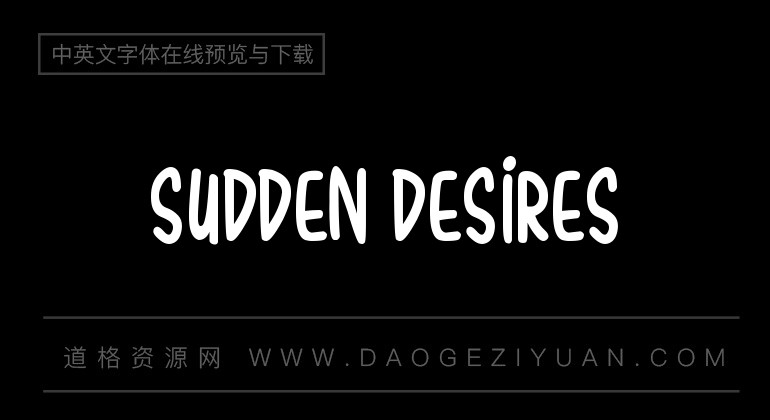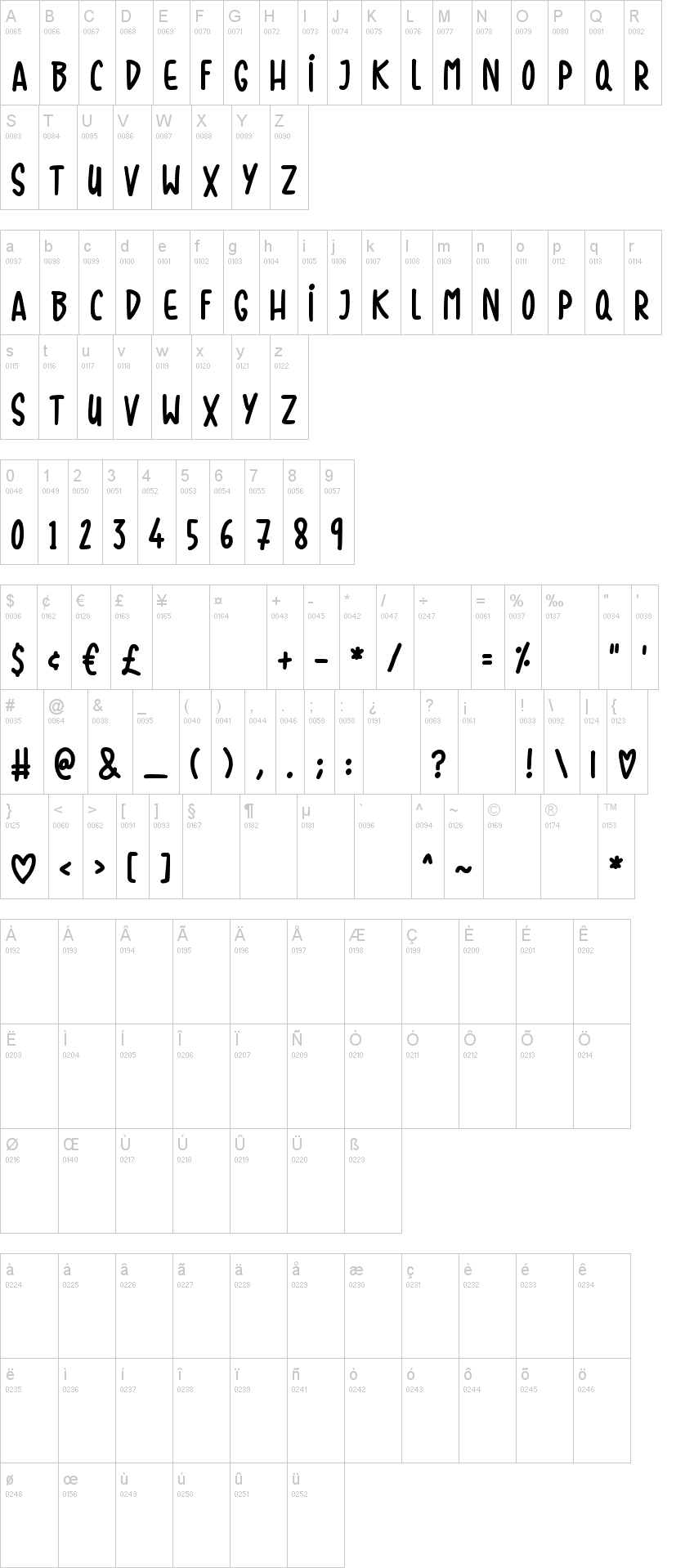
Sudden Desires
Sudden Desires 是一款极具视觉冲击力的手写字体,它具有温暖、自然、灵动的特点,以及细腻的笔触。它的笔画清晰,给人一种自然而又温暖的感觉,使用者可以更轻松地表达出自己的情感。其字体的特点是细节的处理极其精细,给人以温暖、舒适的感觉,使用它可以让你的文字更有表现力。
Sudden Desires是一款非常不错的手写艺术字体,具有很好的视觉感,适合于文化类的宣传设计、商业类品牌的广告和产品包装设计以及个性化文字排版等较多场景。
Sudden Desires字符映射图